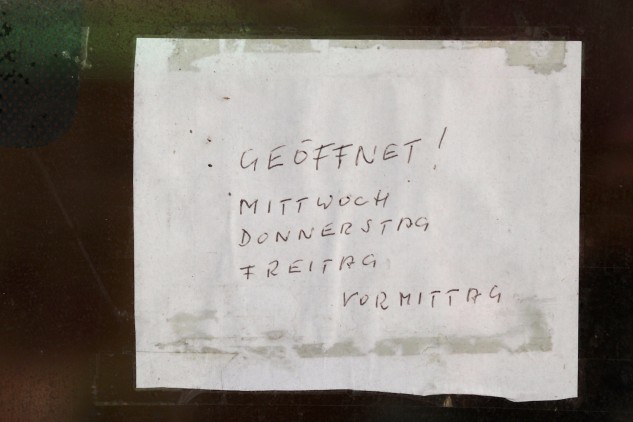
Eingeschränkte Öffnungszeiten Chris Foraita, Wien # 22/07/13 Categories: Freestyle Tags: Handschrift, Hinweis, Mitteilung, Offen, Öffnungszeiten, Sozial, Tageszeit, Versalien, Zettel Waschsalon mit groben Angaben, aber mit Ausdruck. 389 Likes